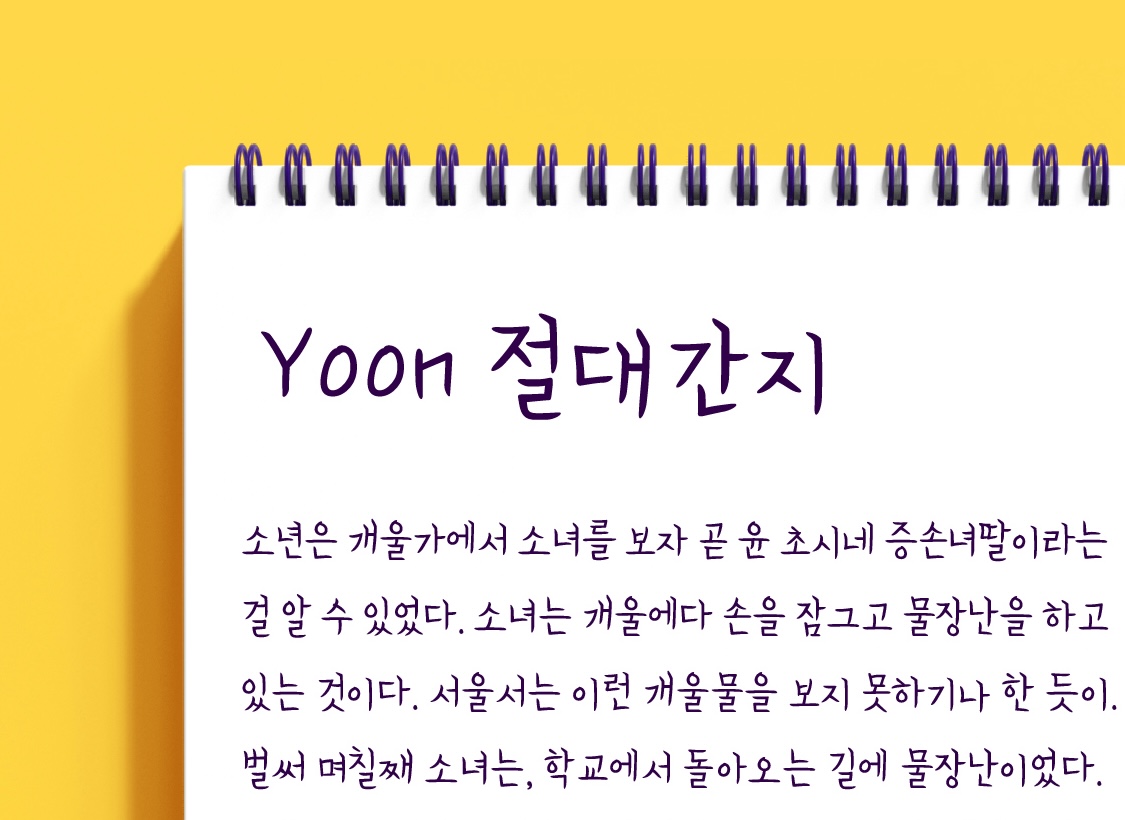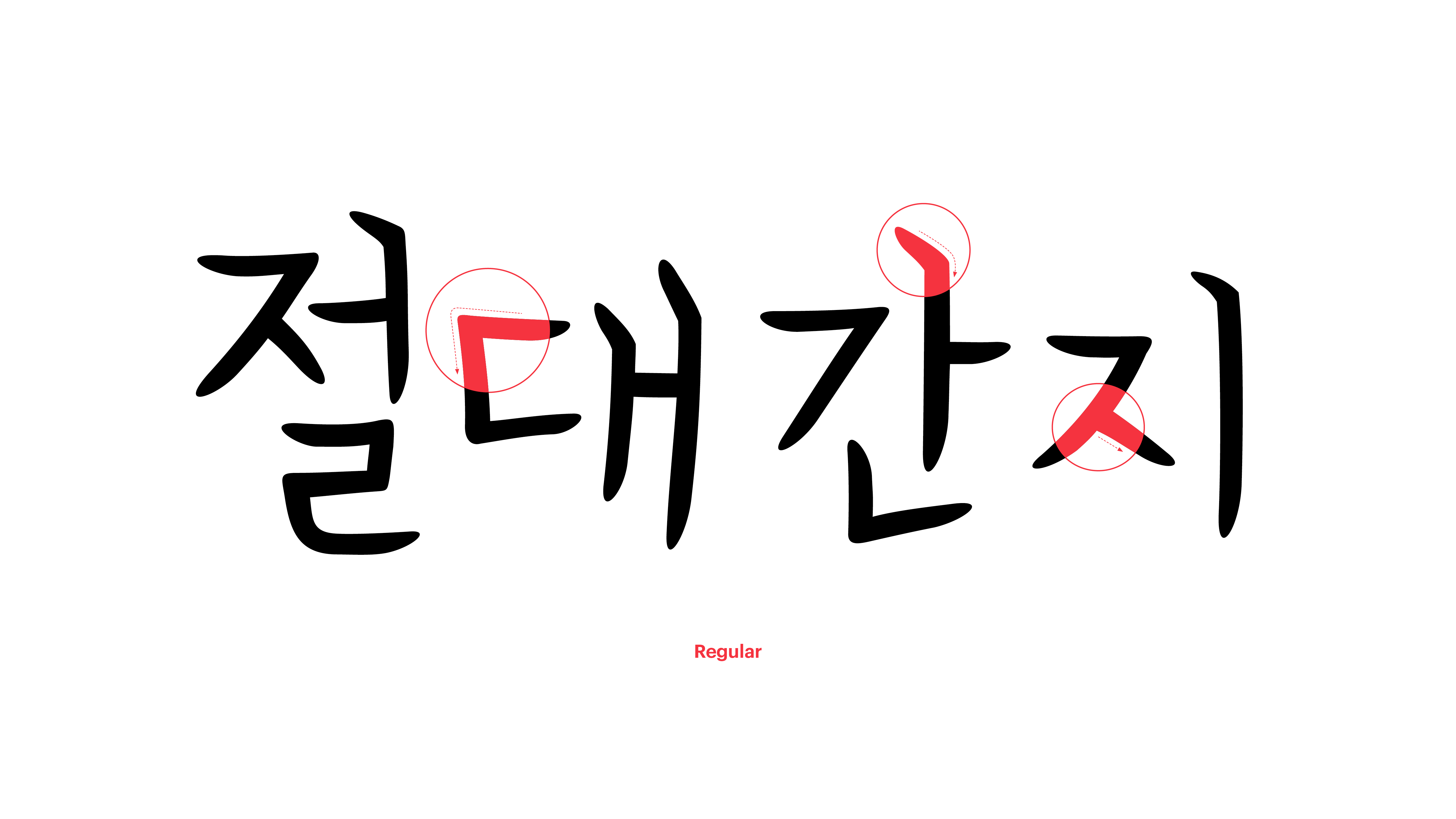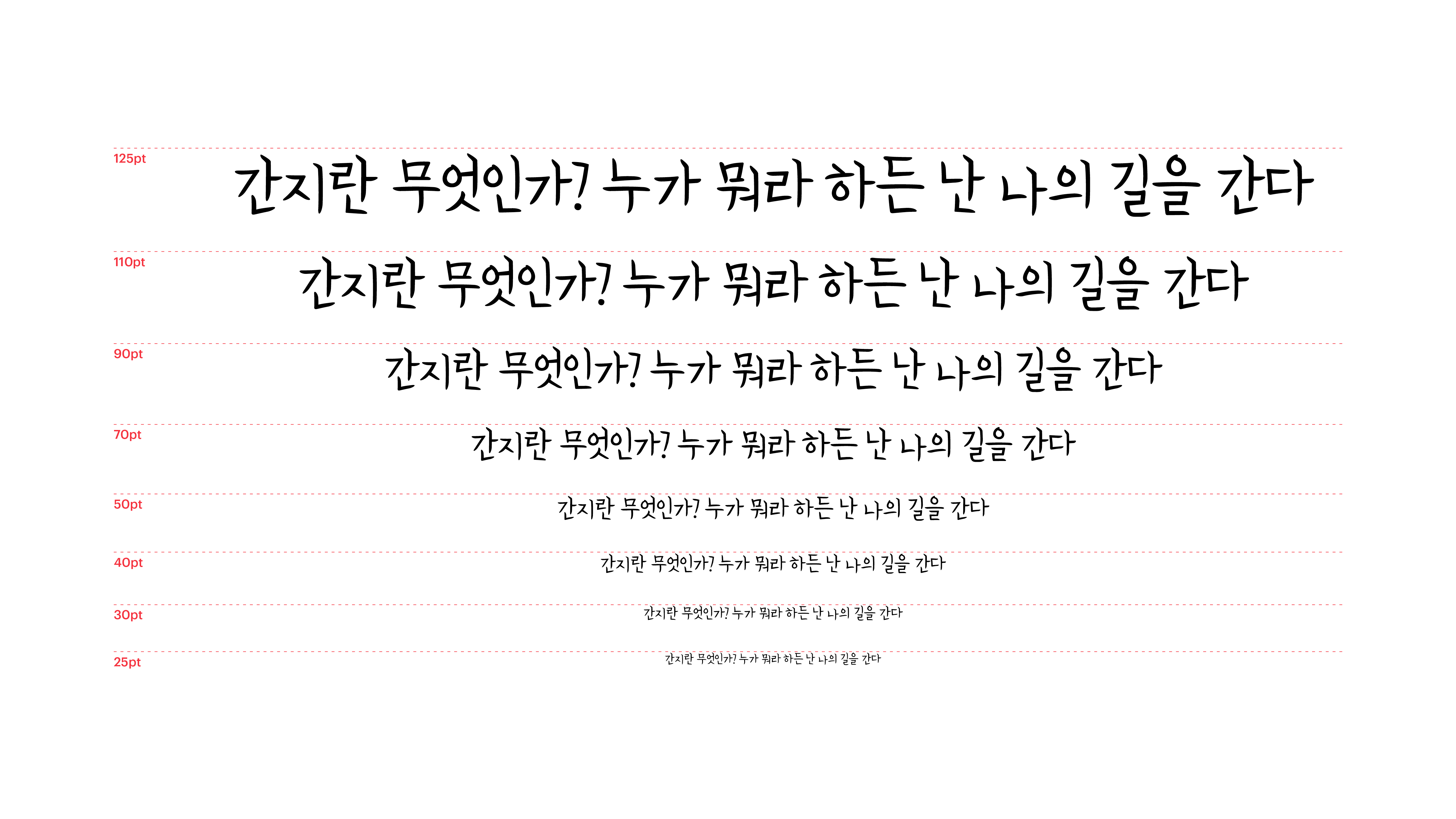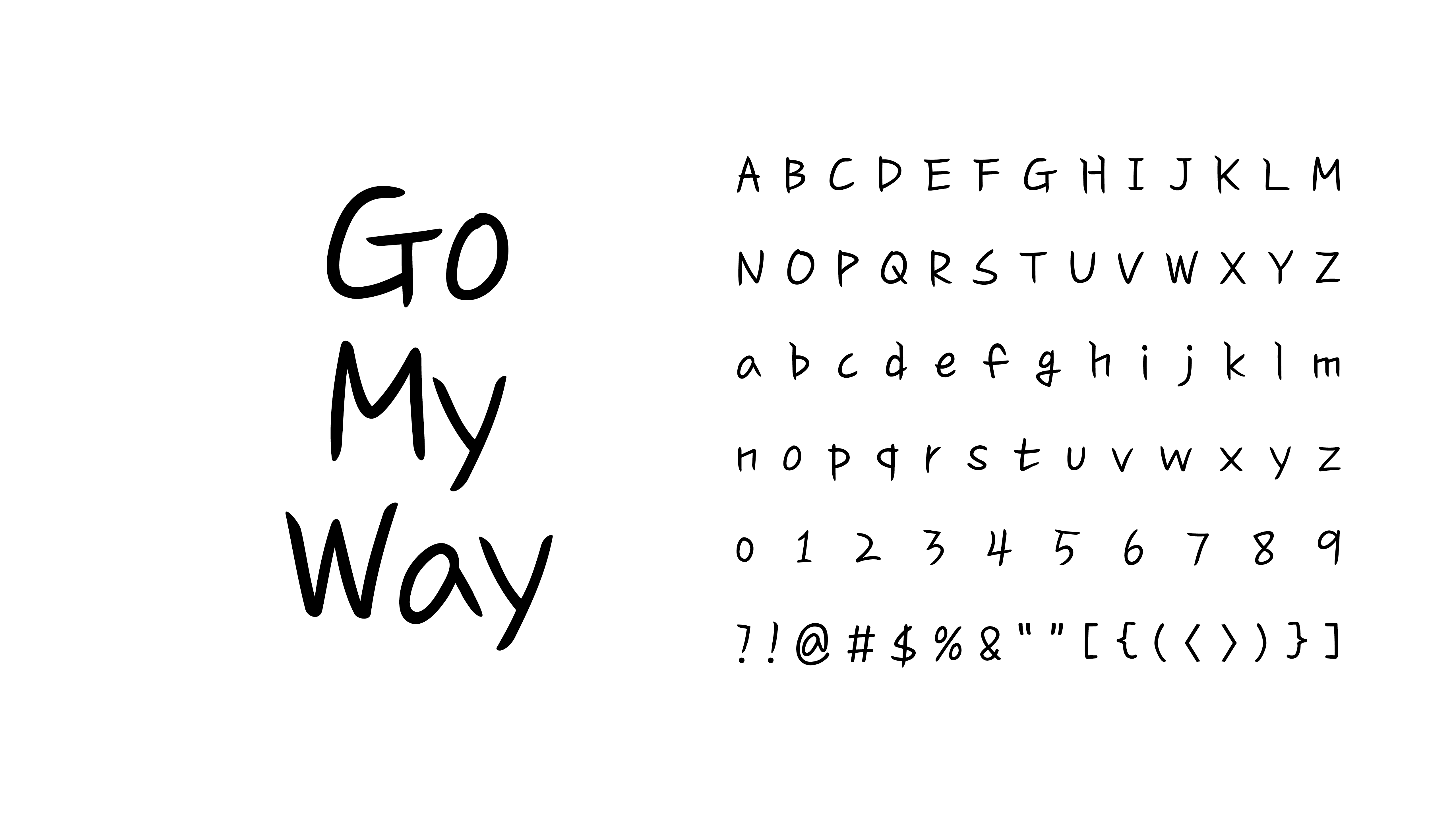
획의 끝을 날카롭게 표현하여 독특한 아우라를 풍기는 폰트입니다. “누가 뭐라 하든 난 나의 길을 간다!” 넘치는 자신감으로 보는 사람들을 전부 매료시킬 것만 같아요. 확신이 없어 하지 못하고 담아만 두었던 말들이 있다면 이 폰트의 힘을 빌려 한 번쯤 당당하게 표현해보세요. 여러분은 여러분이 믿는 것보다 훨씬 더 옳은 사람들이라는 것, 폰코가 말하지 않아도 다 알고 계시죠?
Yoon 절대간지